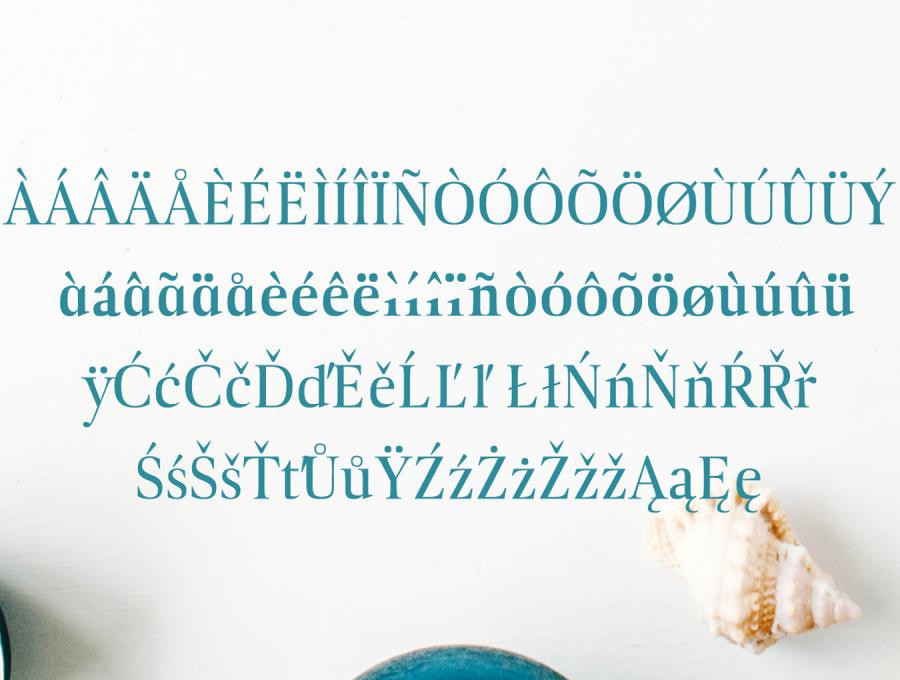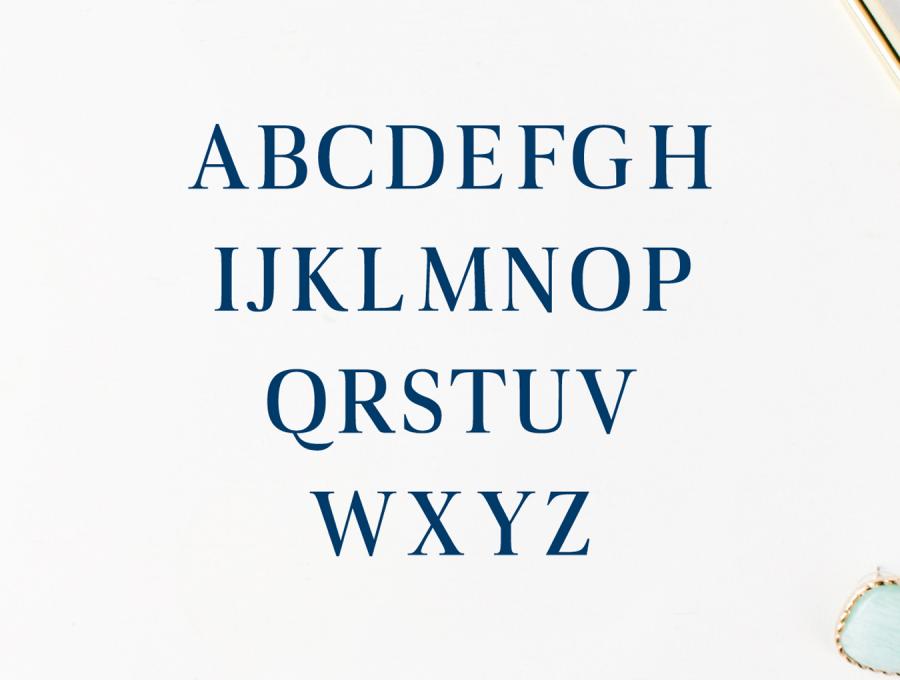
卡拉 英文字体 (Carra Serif Typeface)
Carra Serif 字体是一个最小的干净衬线字体系列,它包含3个重量,它具有独特和现代衬线的外观和感觉。 完美的华丽的标志,标题,网页布局和品牌。 如果你想尝试一个优雅的外观,或者以一个完全永恒的东西,以资本和小写字母为自己的美丽,它在所有的帽子上看起来都很漂亮。